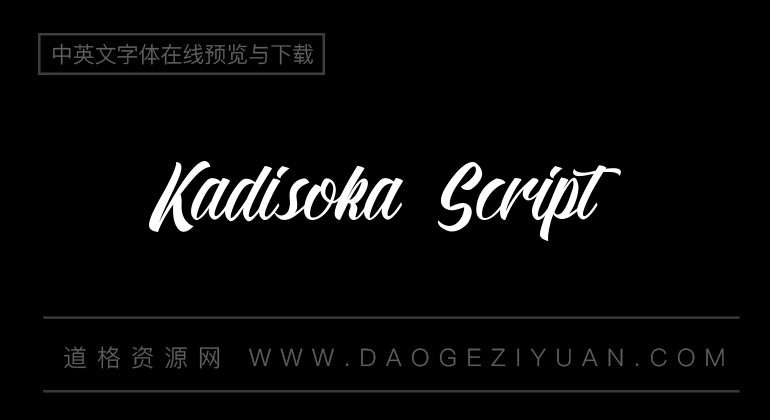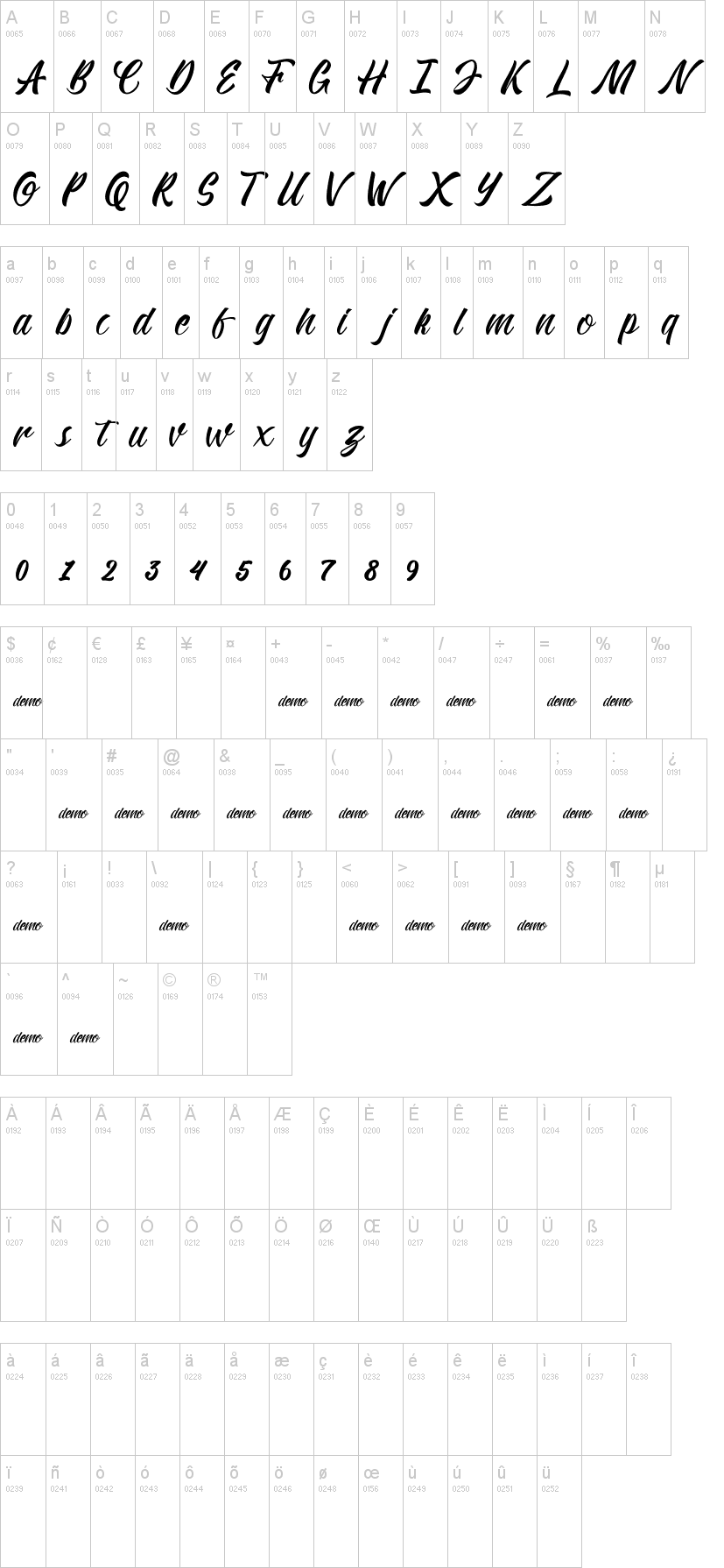
Kadisoka Script
Kadisoka Script 是一款由 Kadisoka 字体库所提供的脚本字体。它是一款具有活力和温暖感的脚本字体,旨在帮助用户营造出更加轻松自然的视觉体验。它的特点是,字体的每一个字母都有着流畅的线条,更加优雅大方,而且每个字母的形状都有着自己独特的设计,使字体更具有个性化的特点。Kadisoka Script 字体的设计风格更加抽象,可以帮助用户创造出更加多样化的绘画效果,使用它可以让你的文字充满生机和活力。
Kadisoka Script是一款非常不错的手写艺术字体,具有很好的视觉感,适合于文化类的宣传设计、商业类品牌的广告和产品包装设计以及个性化文字排版等较多场景。
Kadisoka Script字符映射图